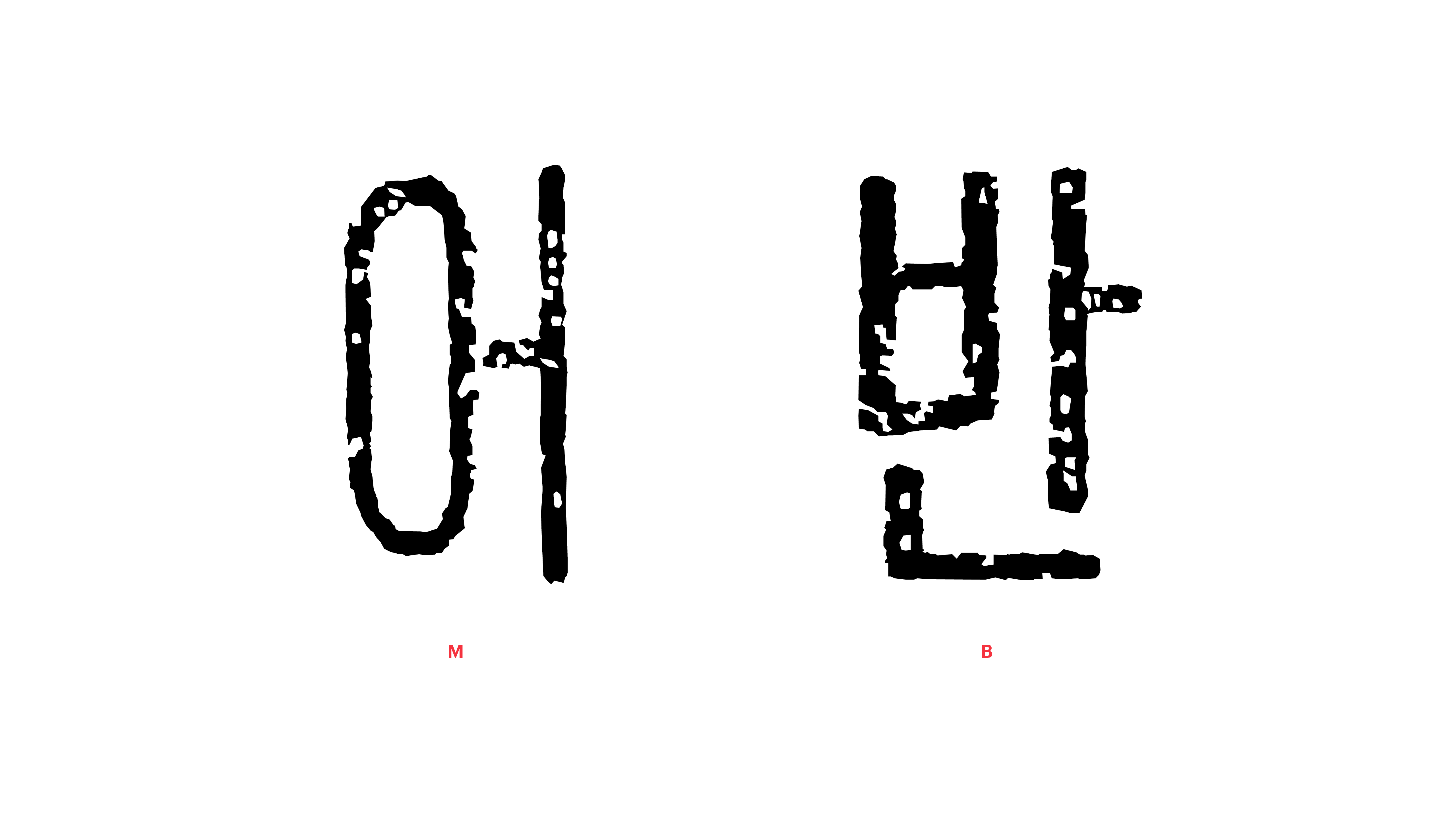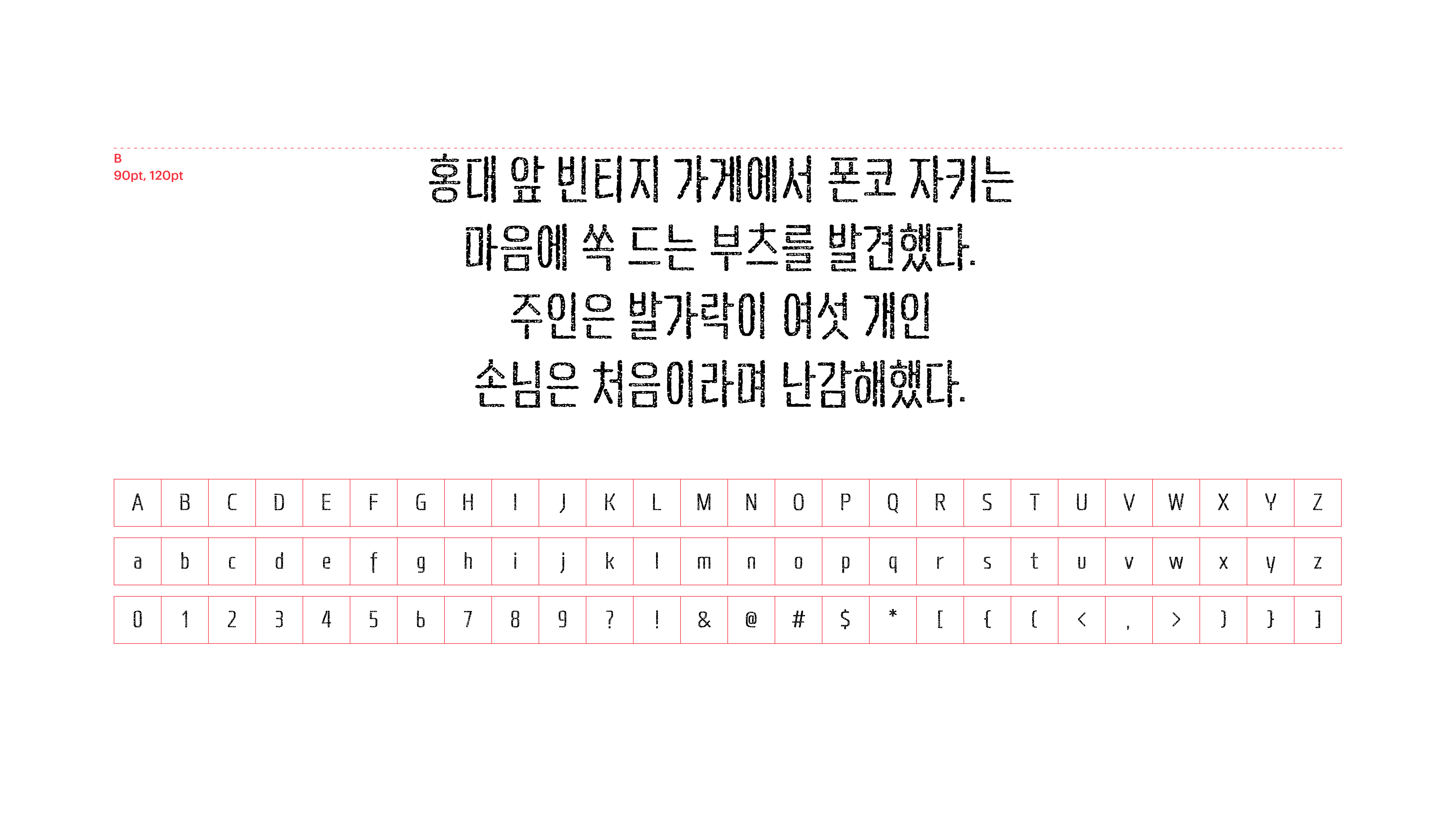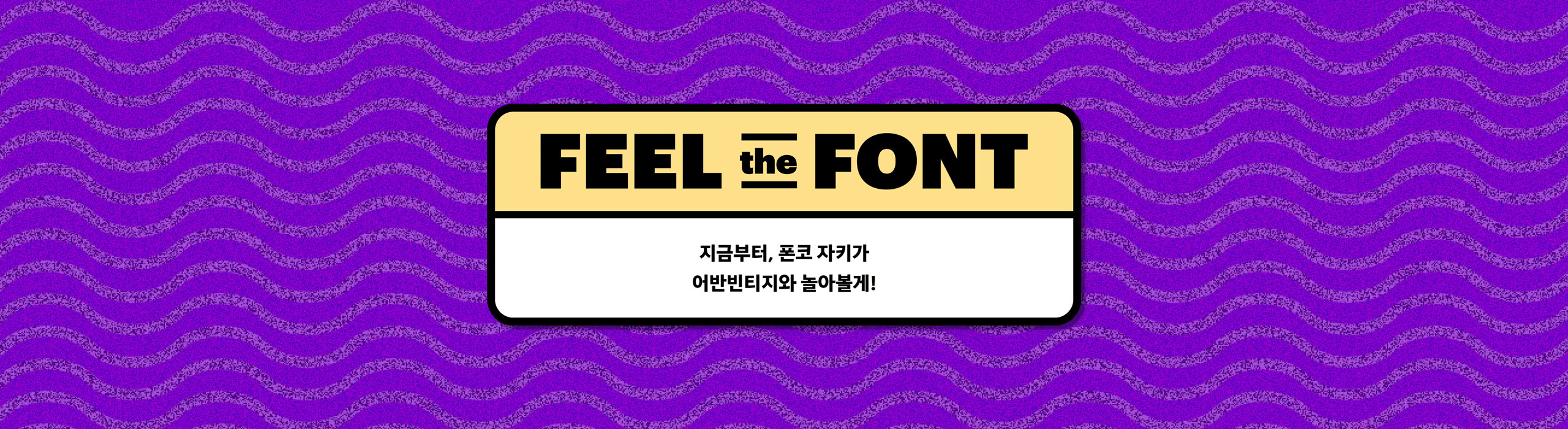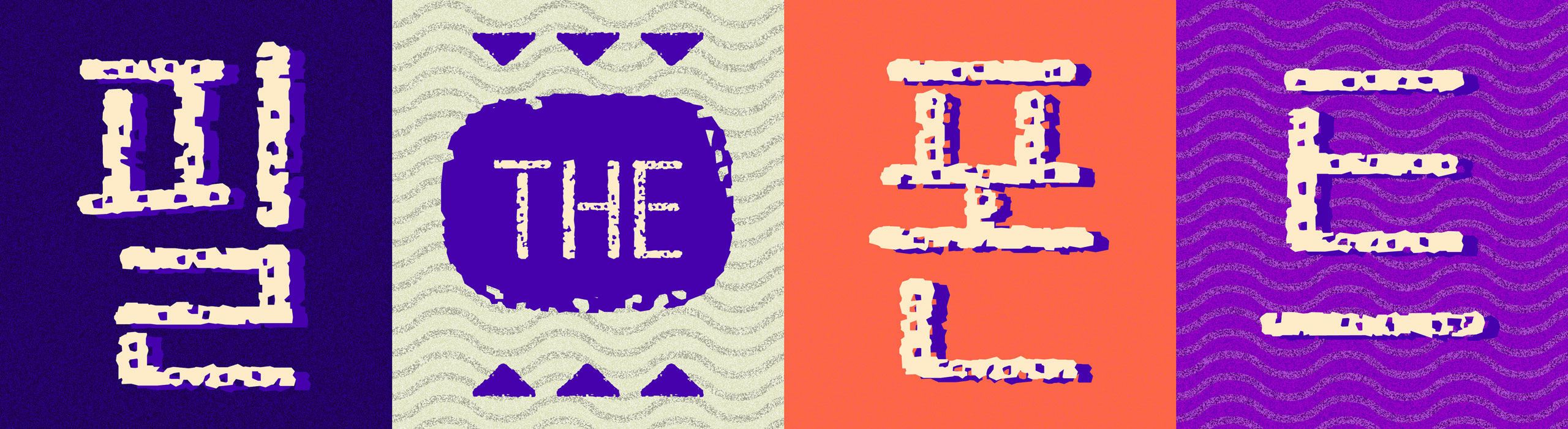
멋지게 낡은 것은 언제나 새것을 능가합니다. 빈티지 감성이 오랫동안 사랑받아온 이유이기도 하지요. 여기, 깔끔한 획을 길쭉하게 늘여 써 시간이 지나도 질리지 않을 것만 같은 폰트가 있습니다. 어딘가 심심해보여서 아스라한 시간의 손때를 멋스럽게 묻혀두었죠. 시간의 소중함을 전하는 질감, 오랫동안 곁에 남아 온기를 전하는 이야기에 잘 어울리는 폰트입니다.
Yoon 어반빈티지